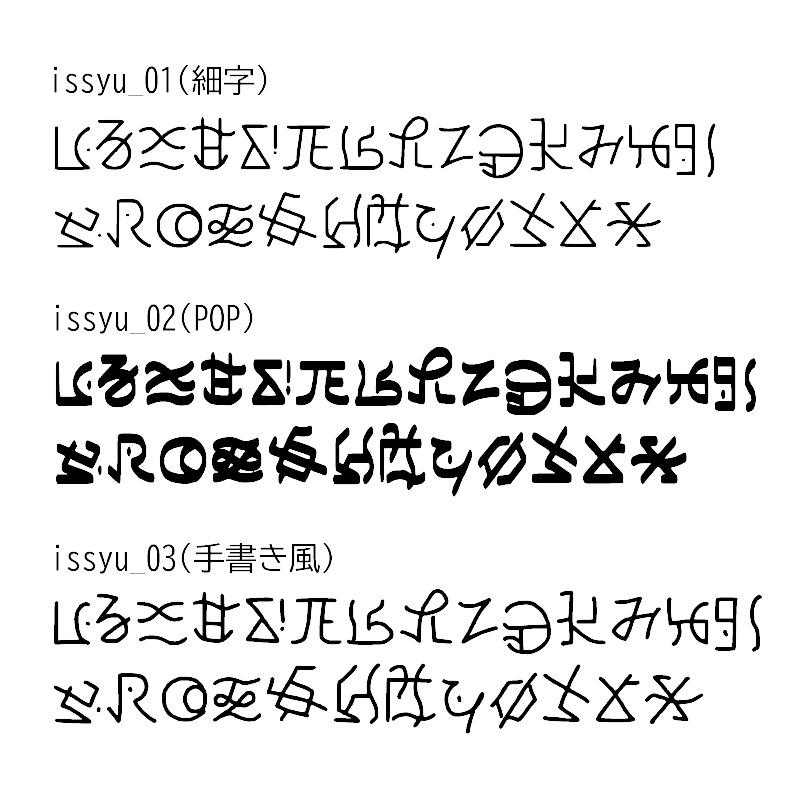
イッシュ文字フォント
2015年発行の同人誌用に作成したイッシュ文字フォントです。 解析された文字は2種類ありますが収録されているのは1種類のみです。 アニポケBW関連のイラストや同人作品などにご自由にお使いください。 半角アルファベット小文字のみ対応(数字はありません)。 細字/POP風/手書き風の3タイプ。 ロゴ風の画像を作成する場合は少し加工した方がキレイに見えます。 <使用上の注意> ・書体をダウンロード、使用したことによるトラブルについて製作者は責任を負いません。 ・公序良俗に反する使用は固く禁じます。 ・著作権は放棄しておりません。 ○創作物への使用 ○同人誌などでの使用 ○個人での使用 ×自作発言 ×商用利用 ×再配布 ×公式が関わるものへの使用 使用時の報告/クレジットはなくても構いません(あると嬉しいです)。 ・pixiv上で使用の際のイメレス先>https://www.pixiv.net/artworks/98329947 ・創作物へのクレジット>pixivID:4462886 2022/05/14